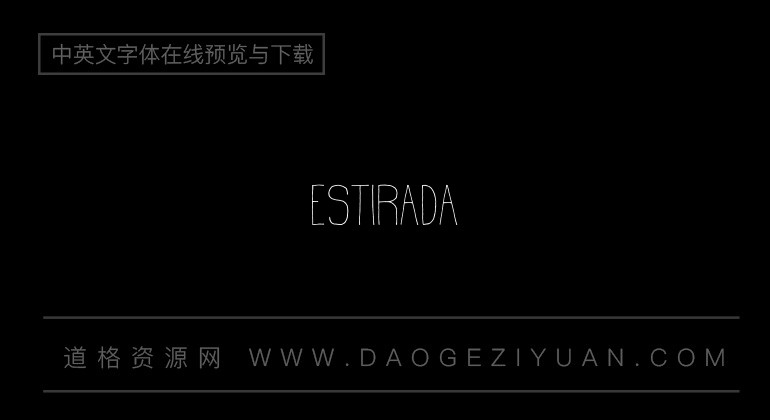
Estirada是一种装饰性的字体,具有非常独特的风格和设计,特别适合用于标题,标语和海报等需要强烈的视觉冲击力的场合。 Estirada的设计灵感来源于欧洲艺术运动和几何学元素,这使得它具有非常流畅的线条和明显的几何图形。这种字体的线条非常细腻,但又不失鲜明,使得它非常适合在大型尺寸的设计中使用。 Estirada字体家族包含多个字重和风格,可以根据需求选择不同的版本。它非常适合用于高端品牌,时尚设计和艺术领域的设计,同时也可以用于电影海报,音乐专辑封面和广告宣传等领域。 总之,Estirada是一个非常具有个性化和独特的字体,能够为设计注入强烈的视觉冲击力,使得设计更加引人注目和令人难忘。内容介绍
Estirada是一款非常不错的手写艺术字体,具有很好的视觉感,适合于文化类的宣传设计、商业类品牌的广告和产品包装设计以及个性化文字排版等较多场景。